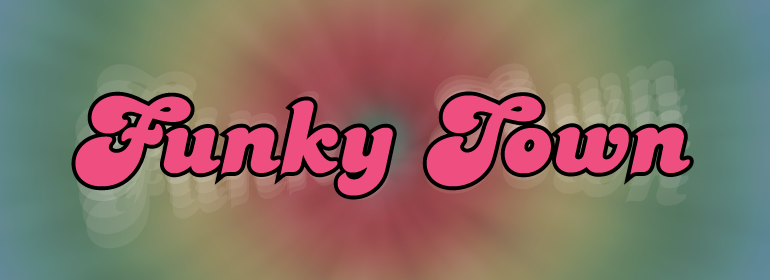
Candice™
Alan Meeks于1976年设计了Candice字体。Candice是一款有趣的漩涡状字体,看起来像一个上面配有鲜奶油的冰淇淋圣代。Candace经常出现在专辑封面上,并且与20世纪70年代无数热门派对歌曲联系到了一起。有一件事是肯定的:Candice是那个时代的产物——华丽、活泼、有趣!
Alan Meeks designed the Candice typeface in 1976. A groovy swirl of a font, Candice looks like an ice cream sundae topped with whipped cream. Candace is often seen on album covers, and has come to be associated with innumerable party hits from the 1970s. One thing is for sure: Candice is a child of it's times - flashy, lively, and fun!